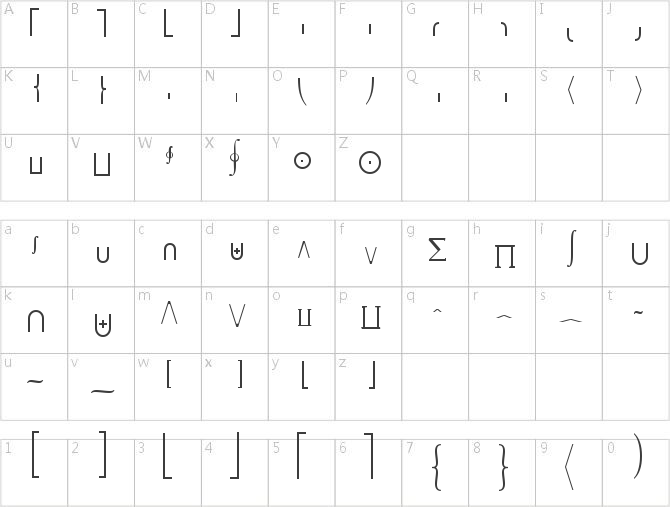
MachadoMathExtensionSSK 詳情頁
MachadoMathExtensionSSK字體字庫是一款讓人賞心悅目、百看不厭的英文字體,適合各類廣告和產(chǎn)品包裝設(shè)計(jì)應(yīng)用,字體大小0.03MB,格式為ttf字體,上傳用戶是sunlight,作者/版權(quán)方為未知